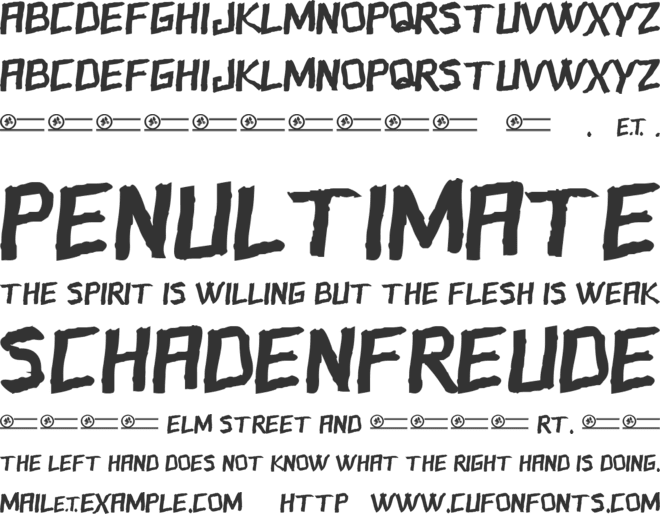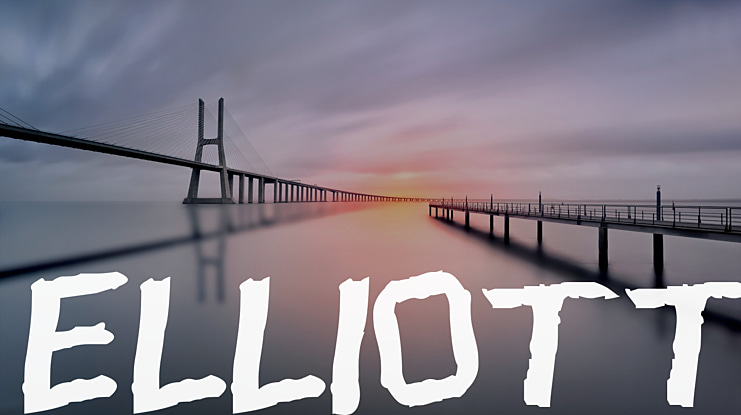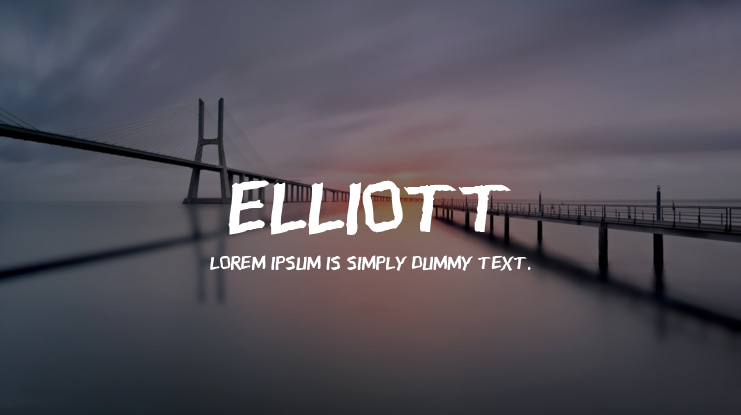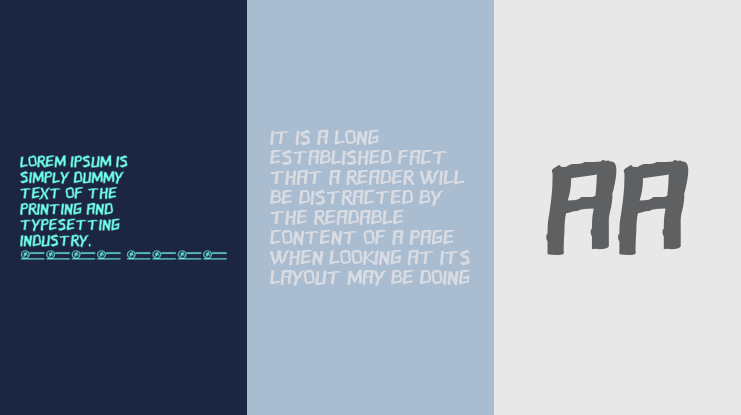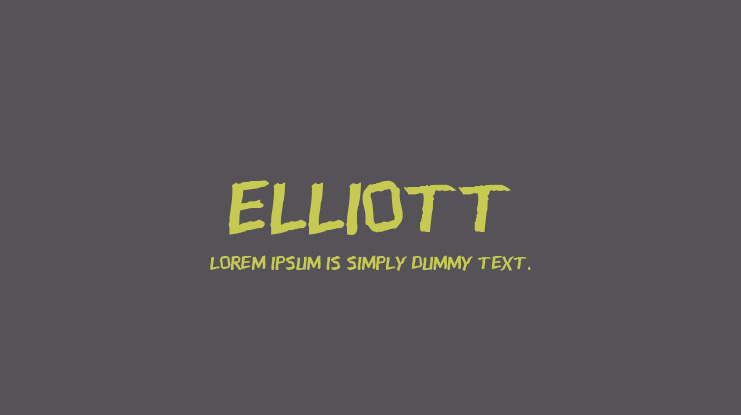
ELLIOTT Font
E.T. font: direttamente dal film diretto da Steven Spieberg e interpretato da Henry Thomas, il font inedito per tutti gli estimatori del film. Da notare il ritocco necessario in Photoshop per conferire, alla titolazione, l'originale bordatura.
E.T. font: directly from the Best movie by Steven Spielberg, with Henry Thomas, the original font for all lovers. Use ADOBE Photoshop for the original border from title.